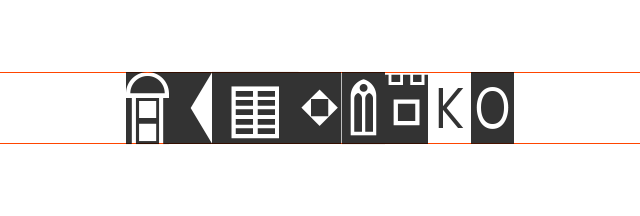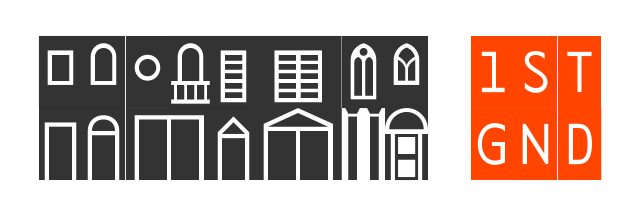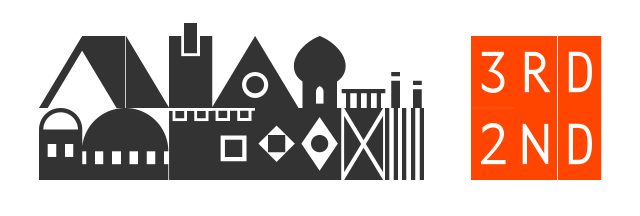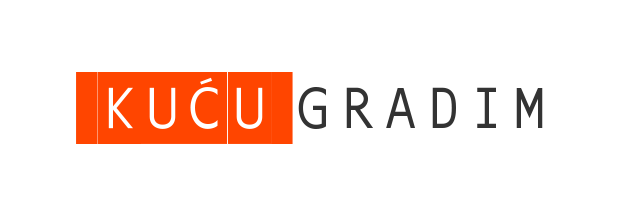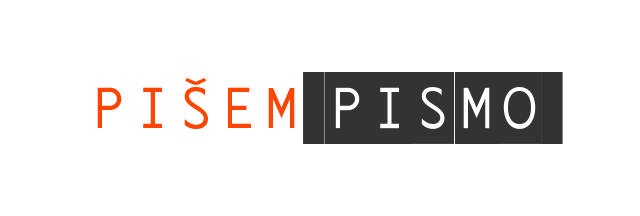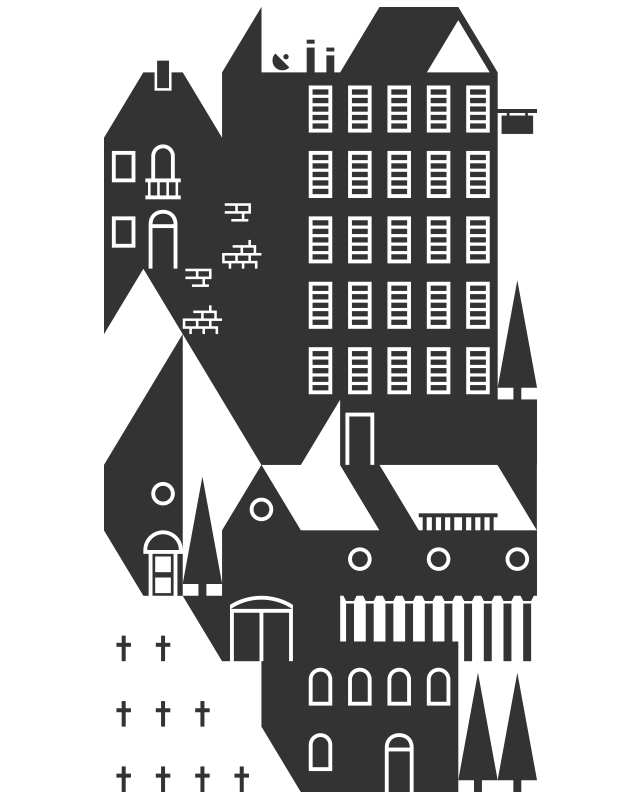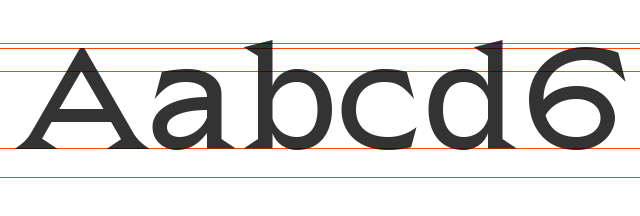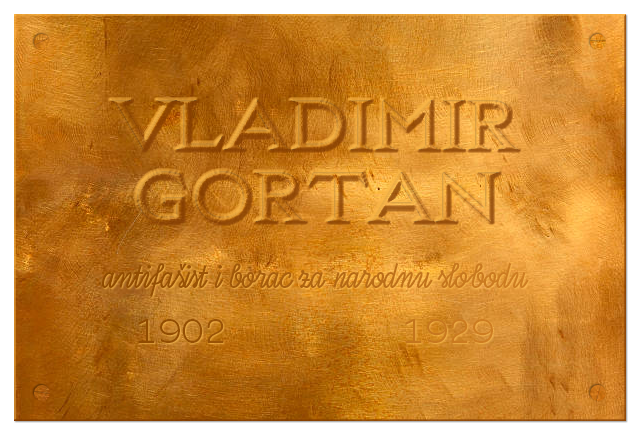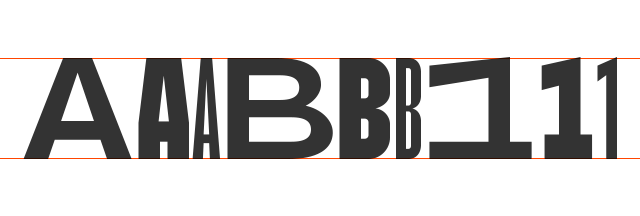
Fzn Frezn
Fzn Frezn je zgodan mali fontić u kojemu je svaki znak iscrtan na novo, bez ikakvih matrica. Sadrži alternative znakove koji ga čine pomalo nasumičnim.
Fzn Frezn is a nice font in which each single character is drawn anew, without the usage of any kind of matrix. It features contextual alternatives as to make it seem more random.
Fzn Monoh
Monospaced tipografsko pismo, kao rukopisno, po uzoru na pisaće mašine. Malo uništen kod prebacivanja (čisto da mu da malo) i pisan je na Note-u. Ima Regular i Regular italic rezove, a ima i stilističke setove. U italicu, osim alt. "a" i "g" može se uključiti i script. Ima i ligature, naravno.
A monospaced typeface, a bit hand drawn, inspired by typewriters. It's a bit messed up by tranfering from one program to another (just to give it an extra kick), and by drawing it on a Note phone. It consists of Regular and Regular Italic cuts, and accompanying stylistic sets. In the italic, besides the alt. "a" & "g", you can turn on cursive "mode". It has ligatures as well, of course.
Fzn Art
Bezkontrastno serifno pismo. Malo inspirirano Copperplateom, malo Gordianom malo raznim renesansnim i ovim novim kao ludim a old skul. Crtano za Nono – art festival fažanske udruge mladih. Za Kasarnu. Ali se vjerojatno neće koristiti za to.
No-contrast serif typeface. It's inspired by these new semi-trash typefaces that are kind of edgy, kind of old school, a bit by Copperplate, a bit by Gordian. Drawn for Fažana Youth Association's art festival &ndsah; Nono. For Kasarna. But it probably won't be used for that.
Fzn Sisé
Sans koji ima regular, regular italic, bold, bold italic i opet sve to za condensed verziju. + display (koji je ful debel).
Sans that consists of regular, regular italic, bold, bold italic, and all these cuts for the condensed version as well. + display (which is very fat).
Fzn Artija
Bezkontrastno monospaced sans serif. Ima tri širine znakova. Crtano za Arterija festival. Fzn Artija Streets ima znakove za crtati kao karte.
No-contrast monospaced sans serif. It has three widths for each glyph. Drawn for Arterija festival. Fzn Artija Streets has glyphs with which you can draw some maps.
Fzn Vi
Crtan po par znakova sa nekog novčića ili tako nečeg. Čudan. Ima nešto alternativnih znakova, nema kurenata, ali ima dosta uzoraka.
Drawn from a few glyphs found on a coin or something like a coin. Peculiar. It features some alternative glyphs, no lowercase, and a lot of patterns.
Fzn Line
Tipografsko pismo crtano kako bi stvaralo neku teksturu (jer slovima treba gledati kakvu teksturu tvore, zato se i zove tekst(ura)). U biti ne niti teksturu, nego samo linije kao plceholder text. Slabo-do-ne čitljivo. Ali kul izgleda. Ima 3 reza: popunjeno (regular), izbušeno (medium) i rupe (bold). Tako da se može i kombinirati, još ako nabaciš neki offset na jednom sloju izgleda sasvim solidno.
Typeface drawn as to make a texture (beause you have to look at the text texture, that's why it's called text(ture)). Well not as much a texture as just some lines for placeholder text. Low-to-no readability. But it looks cool. It contains 3 cuts: filled (regular), punctured (medium) & punctures (bold). So you can combine them, and if you offset one of the layers it looks pretty decent.
Fzn Italo
Kontrastno serifno pismo translacijske konstrukcije. Fazan fontovi baš i ne pokrivaju italic, a italic ti često treba za prelom i šta god. Ovo je 2. iz serije italic Fazan fontova. Ima nešto zanimljivih detalja (e, k, y, K, Y). Možda je i malo kaligrafski.
Broad nib pen contrast serif typeface. Fazan Fonts don't cover the italic spectrum well, and one needs italics when working with books and what not. This is the 2nd typeface from the italic series. It has some interesting details (e, k, y, K, Y). It's a bit caligraphic as well.
Fzn Jednak
Monospaced fontić sa nekoliko alternativnih znakova. Geometrijke konstrukcije. Ima ligatura, lijepo se ponaša u tekstu, iako daje jaaako svijetlu teksturu. Dosta je tanak i prozračan. Djeluje mehanički, ali i nekako prirodno. Ima malo neočekivano "s".
A monospaced little bugger with a few alternative glyphs. Geometric construction. It features ligatures, and behaves in running text, although it gives a veeery light texture. It's quite thin and airy. Feels mechanic, but at the same time somewhat natural. Ah, and it has an unexpected "s".
Fzn Kasarna Stencil
Debeli stencil, samo verzale, poprilično ligatura. O.K. je. Dobro izgleda kad ima masu teksta. Ima foru da slova kao nestaju, rastavljaju se/raspadaju kao.
A fat stencil, uppercase only, with quite a few ligatures. It's O.K. I guess. It looks good when there's a lot of txt. There's an OpenType (calt) feat you can turn on – to make the letters disappear/get deconstructed.